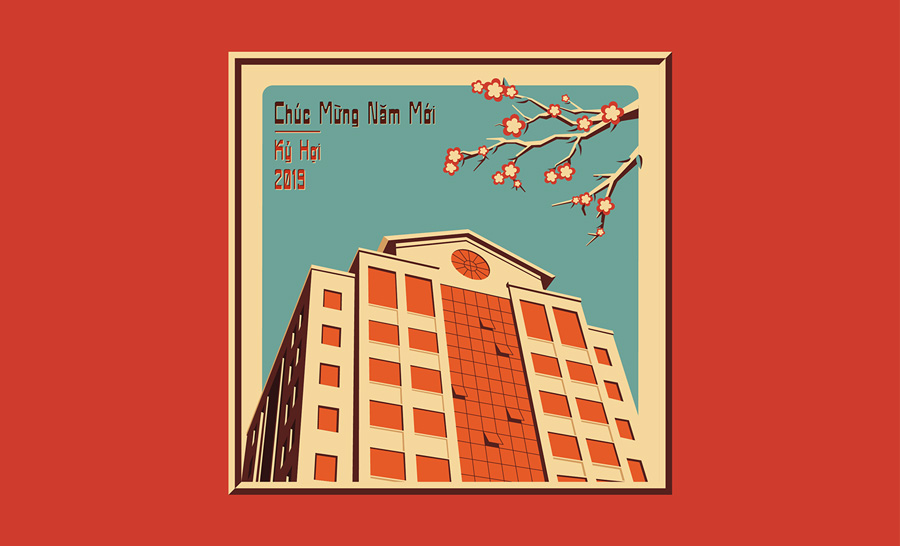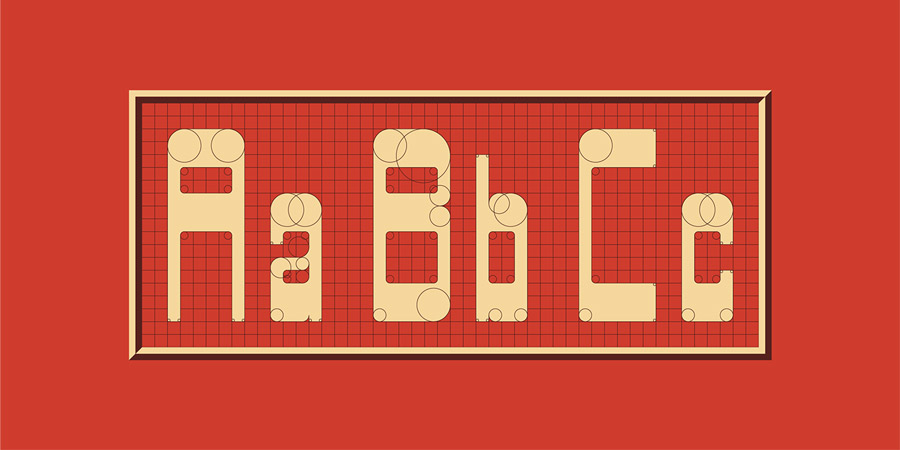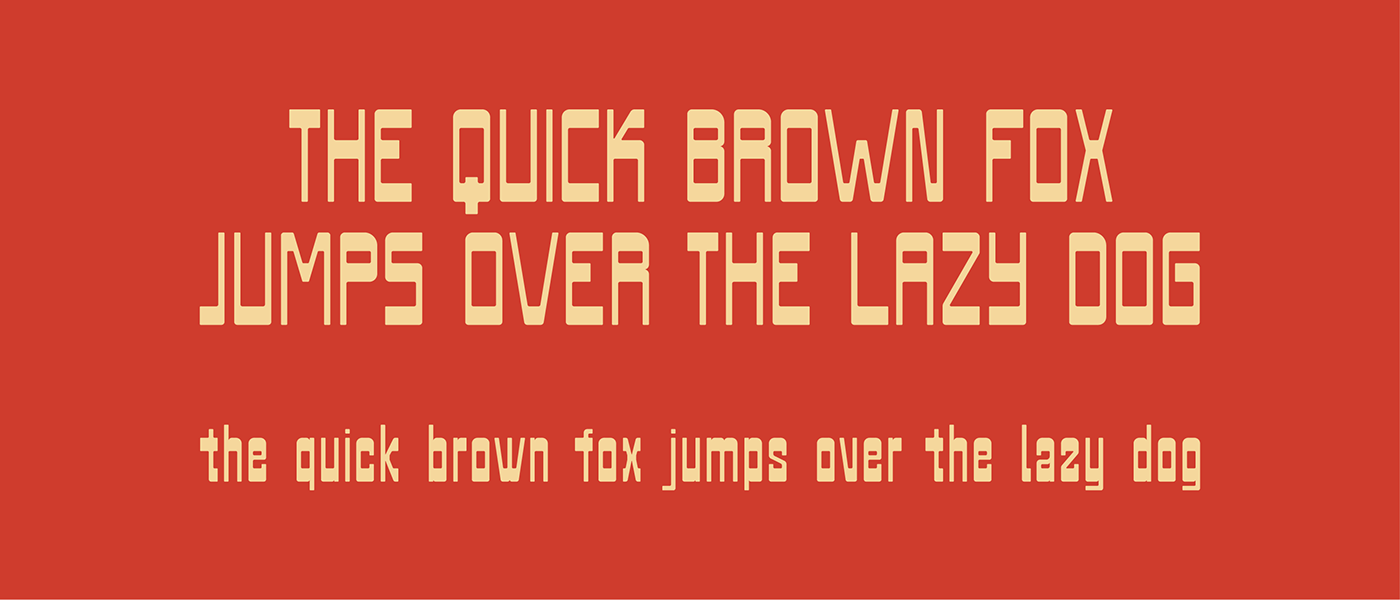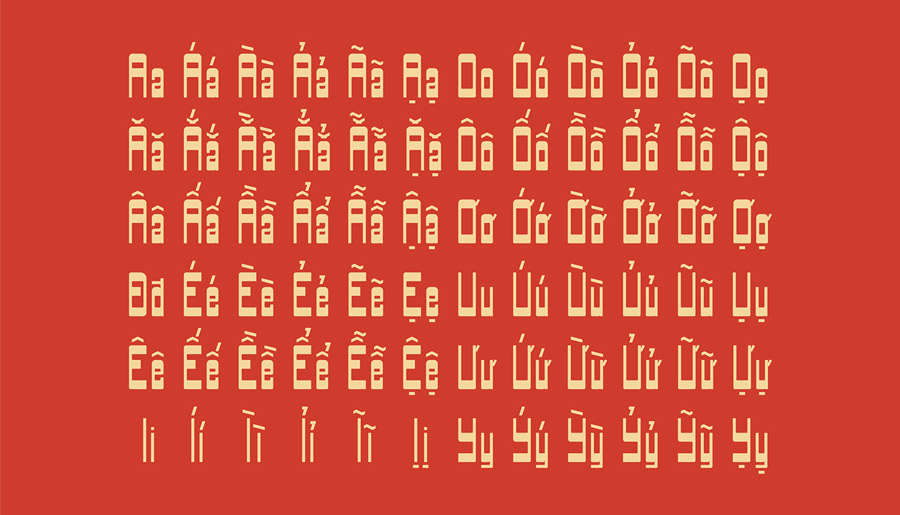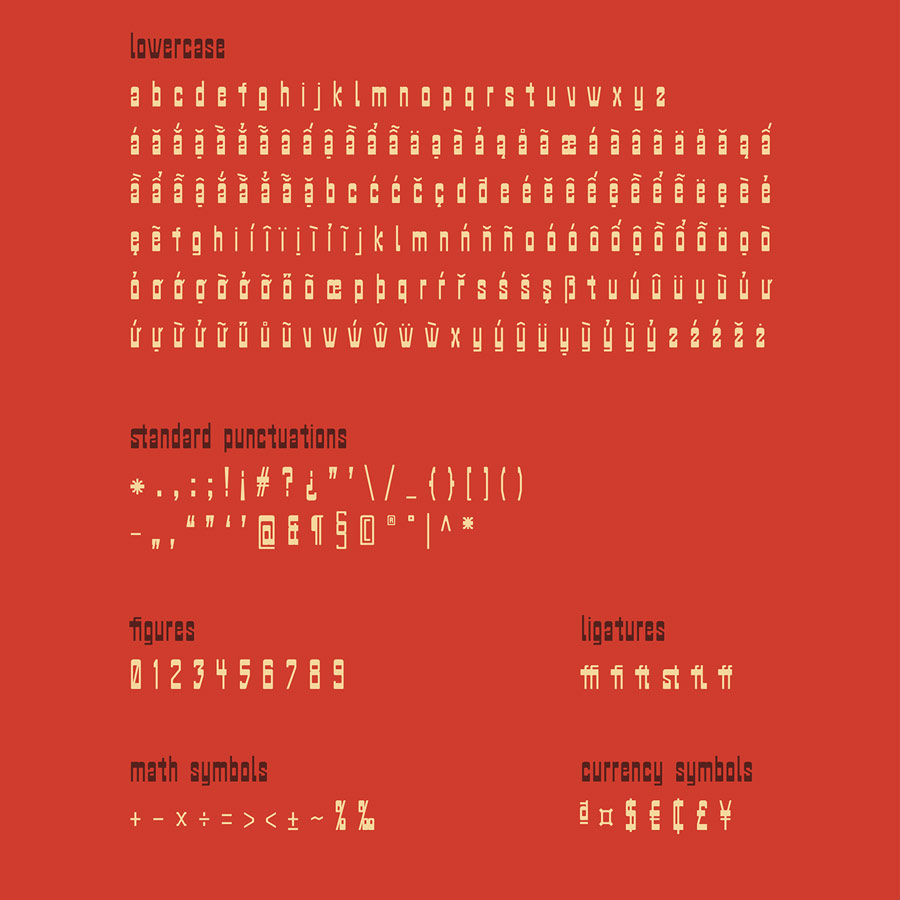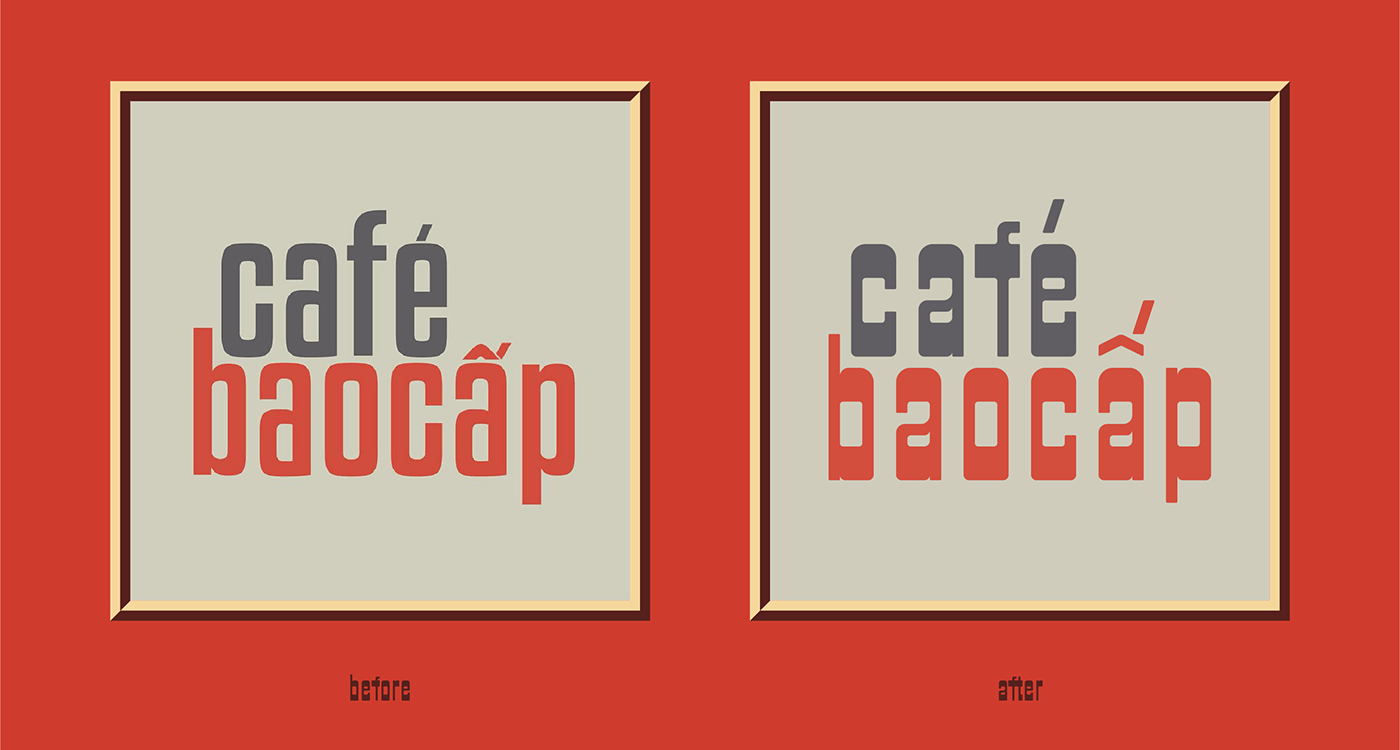
Mời tải font chữ Bìa sách xưa, mang phong cách hoài cổ độc đáo, có hỗ trợ tiếng Việt
Font chữ Bia Sach Xua do tác giả Tống Văn Hiệp phát triển dựa trên ý tưởng từ những tấm banner quảng cá, bìa sách cũ, lâu đời của Việt Nam từ những năm 1980. Font chữ này mới chỉ được phát hành vào đầu tháng 1 và có hỗ trợ tiếng Việt.
Kiểu chữ này mang phong cách hoài cổ với đường ngang dày còn các nét thẳng thì thanh mảnh. Nếu yêu thích và muốn thiết kế ra những tác phẩm mang phong cách hoài cổ, các bạn có thể truy cập vào link dưới đây để tải về.